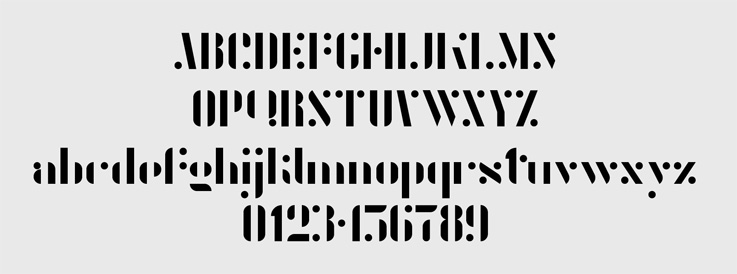
Ésta tipografía gratuita Stencil diseñada por Mark O’Neill pretende ser un reto en cuánto a legibilidad se refiere, ya que inhibe partes de la letra para crear un diseño moderno y rompedor.
Es una tipografía minimalista, inspirada por los trabajos de Le Corbusier, y que Mark incluyó dentro de un proyecto de 4 semanas de duración que nombró como “envisage”.
This free Stencil typography designed by Mark O’Neill aims to be a challenge in terms of readability, since it deletes parts of the letter to create a modern and groundbreaking design.
It is a minimal stencil display typeface inspired by clear simplistic geometric forms and structures envisaged by Le Corbusier. The font was created for a 4 week project under the name ‘envisage’.